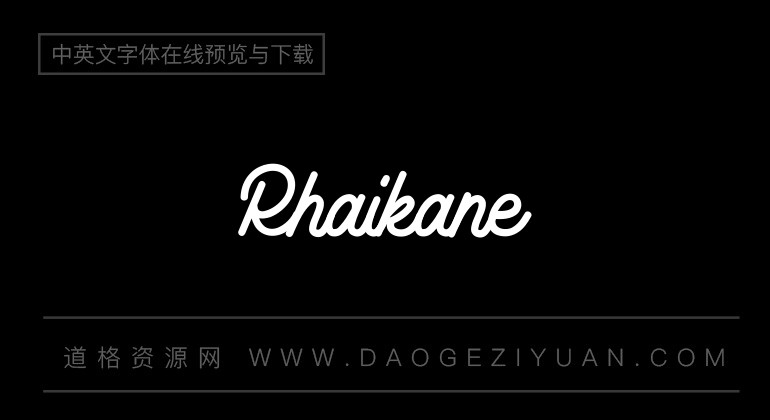
Rhaikane 是一款由著名设计师和字体设计师罗伯特·拉维克(Robert Lavek)设计的字体,它是一种英文字体,具有细腻的线条,清新自然的外观,具有良好的可读性,适合用于各种文档和平面设计中。Rhaikane 字体的特点是它的简洁大方,可以很好地表达深刻的意义,它的字形简单,并且可以很容易地进行混搭,与其他字体结合使用,可以让您的设计更加有趣。内容介绍
Rhaikane是一款非常不错的手写艺术字体,具有很好的视觉感,适合于文化类的宣传设计、商业类品牌的广告和产品包装设计以及个性化文字排版等较多场景。